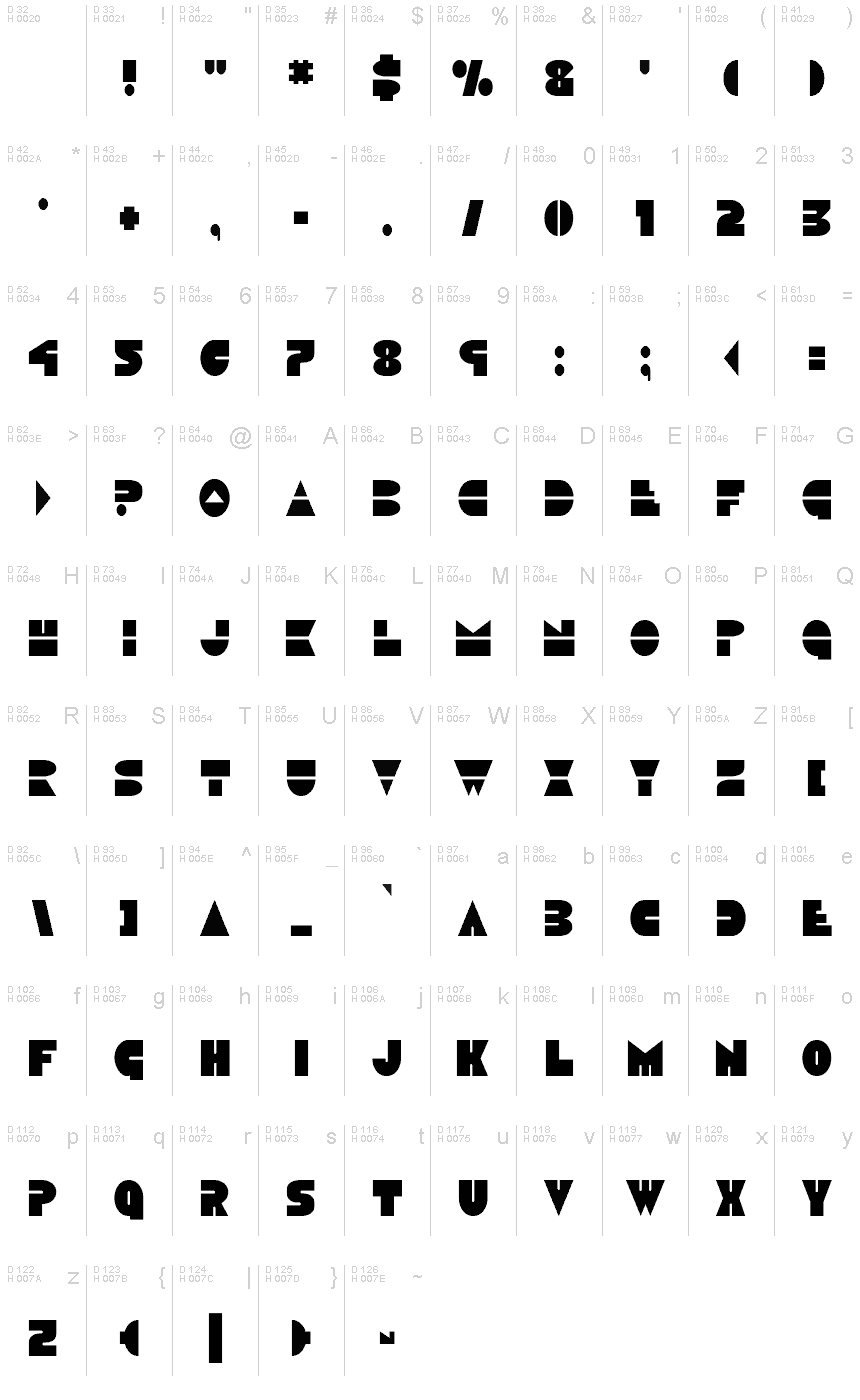
Disco Duck Condensed da Iconian Fonts é uma fonte display gratuita e cheia de groove, que reúne letras modulares e robustas em um ritmo vertical bem justo. Cada caractere parece um bloco iluminado por neon, cortado com precisão por traços horizontais ousados que criam um efeito de listras integrado. A largura condensada mantém as palavras altas e impactantes, fazendo com que até títulos curtos pareçam vibrantes, empilhados e prontos para a pista de dança.
Com Disco Duck Condensed, você garante instantaneamente aquela energia de clube retrô para flyers de festas, pôsteres de DJs ou festivais, capas de álbuns e mixtapes, títulos de jogos, logotipos marcantes e artes para YouTube ou Twitch. O espaçamento justo e os traços grossos mantêm a legibilidade em tamanhos grandes, seja na tela ou no papel, atraindo atenção à distância. Esta fonte gratuita combina perfeitamente com uma sem serifa simples e aberta para o texto principal — deixe a Disco Duck comandar as manchetes enquanto o texto de apoio permanece limpo e discreto.